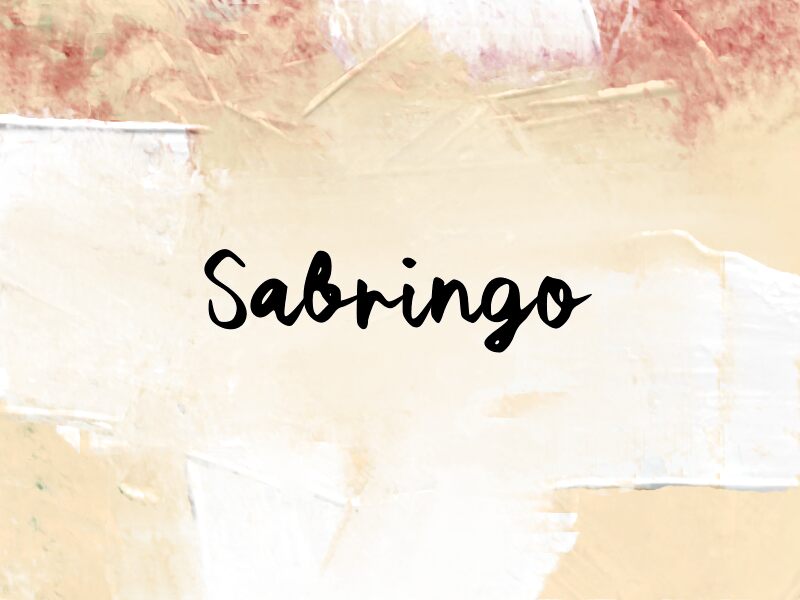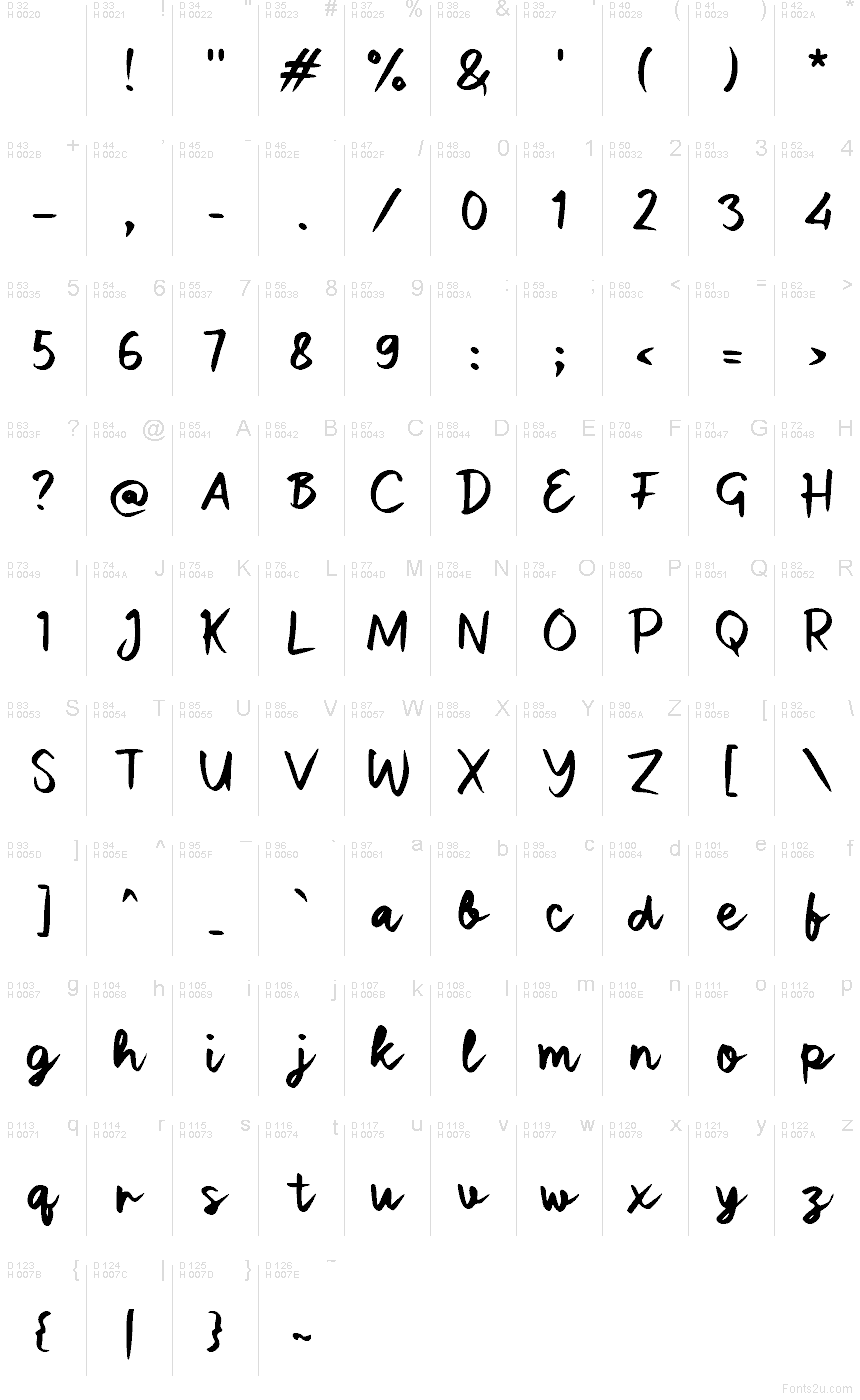
Sabringo
Sabringo, da Wep, é uma fonte manuscrita gratuita com um ritmo de brush-script solto que sobe e desce em traços rápidos e confiantes. As alças altas, as curvas arredondadas e o fluxo levemente irregular dão às letras um toque pessoal e fresco, sem aquele aspeto excessivamente polido das escritas formais.
Esse movimento leve torna a fonte perfeita para menus de cafés, embalagens de produtos, frases para redes sociais, cartões de felicitações e logotipos informais. Também é uma excelente escolha para títulos de cartazes e sinalização de eventos, onde um estilo manuscrito e amigável torna a mensagem mais direta e próxima.